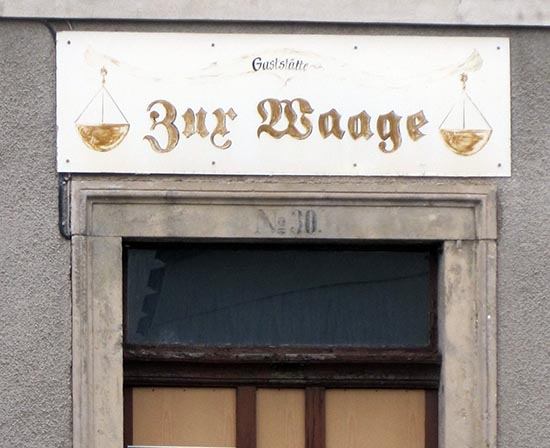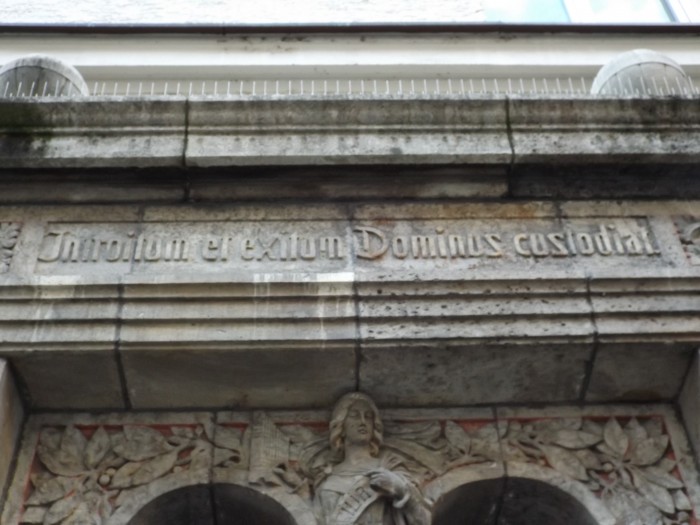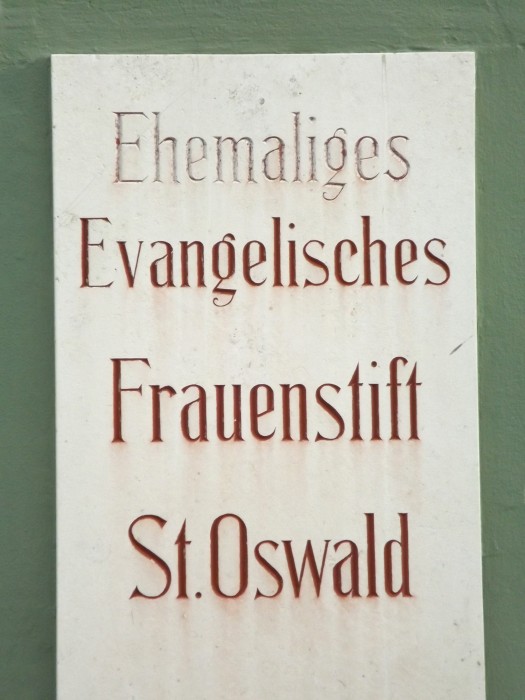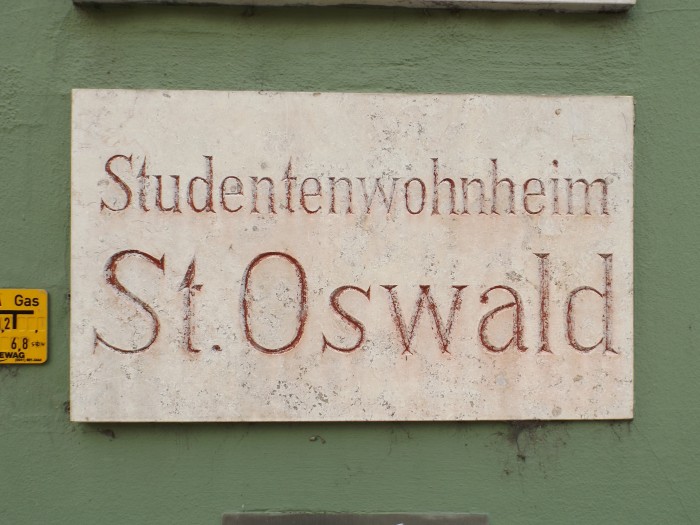
Typostreifzug durch die Stadt ...
echte Schätze im Archiv versteckt
was heißt hier ›versteckt‹?
Ja, ich sammle mit der Zeit an, was so unter die Linse kommt.
Manchmal sind es auch BESONDere Köstlichkeiten:
Oder Sturm.
nein, das ist alles so befestigt worden. Mit Absicht und Bohrmaschine.
In mein Grausen mischt sich, oh wahn, ein wenig Neid.
nein, das ist alles so befestigt worden. Mit Absicht und Bohrmaschine.
In mein Grausen mischt sich, oh wahn, ein wenig Neid.
Sollen wir für eine Bohrmaschine zusammenlegen?
nein, das ist alles so befestigt worden. Mit Absicht und Bohrmaschine.
In mein Grausen mischt sich, oh wahn, ein wenig Neid.
Da fällt mir der Slogan eines Baumarktes ein: »Mach’ es zu Deinem Projekt!«  :cheer:
Hier waren bestimmt einige Promille am Werk.
Spannend wäre auch die Frage, wann das montiert wurde und ob es immer noch so hängt oder ob der Zuständige offensichtlich Dauer-Promille haben müsste ... ;-)
Vor einiger Zeit mal fotografiert …
An diesem Schild bin ich nun seit über zehn Jahren fast jeden Tag vorbeigefahren. Aber erst seit ich mich für Typografie interessiere, ist es mir aufgefallen. Ich finde es ziemlich hübsch.
(Runde!) Grotesk auf einem Fraktur-Skelett – sehr schick! Ist aus der Zeit um die Jahrhundertwende, wie ein weiterer Schriftzug weiter unten verkündet.